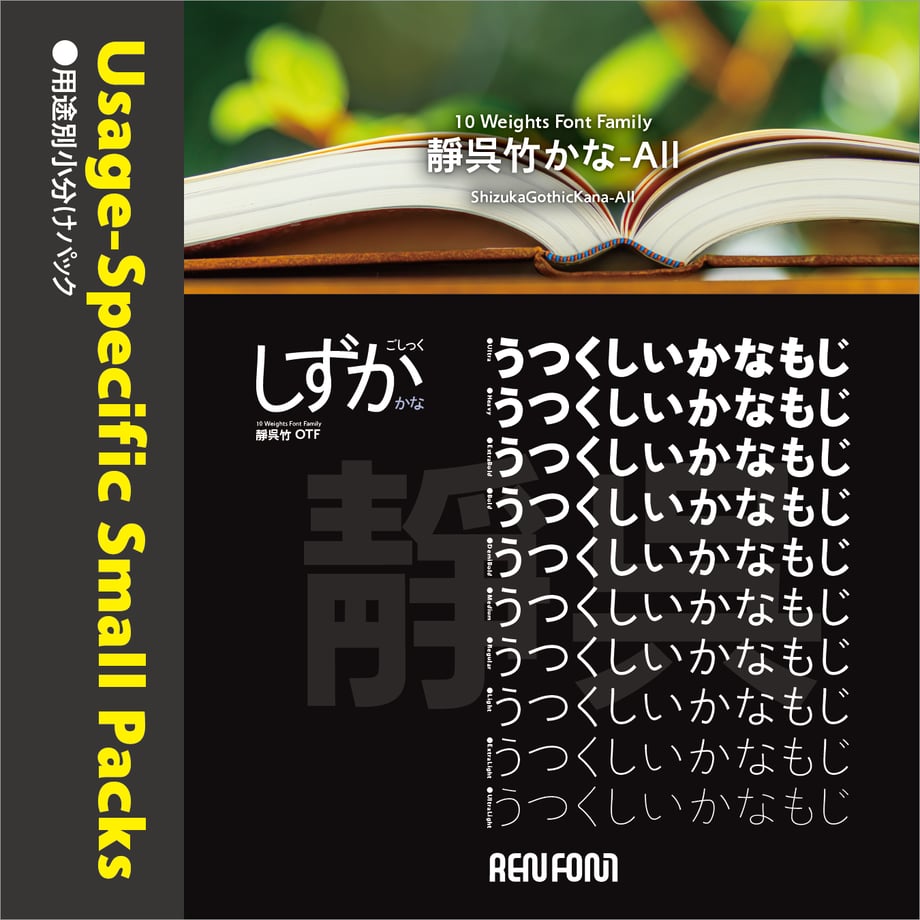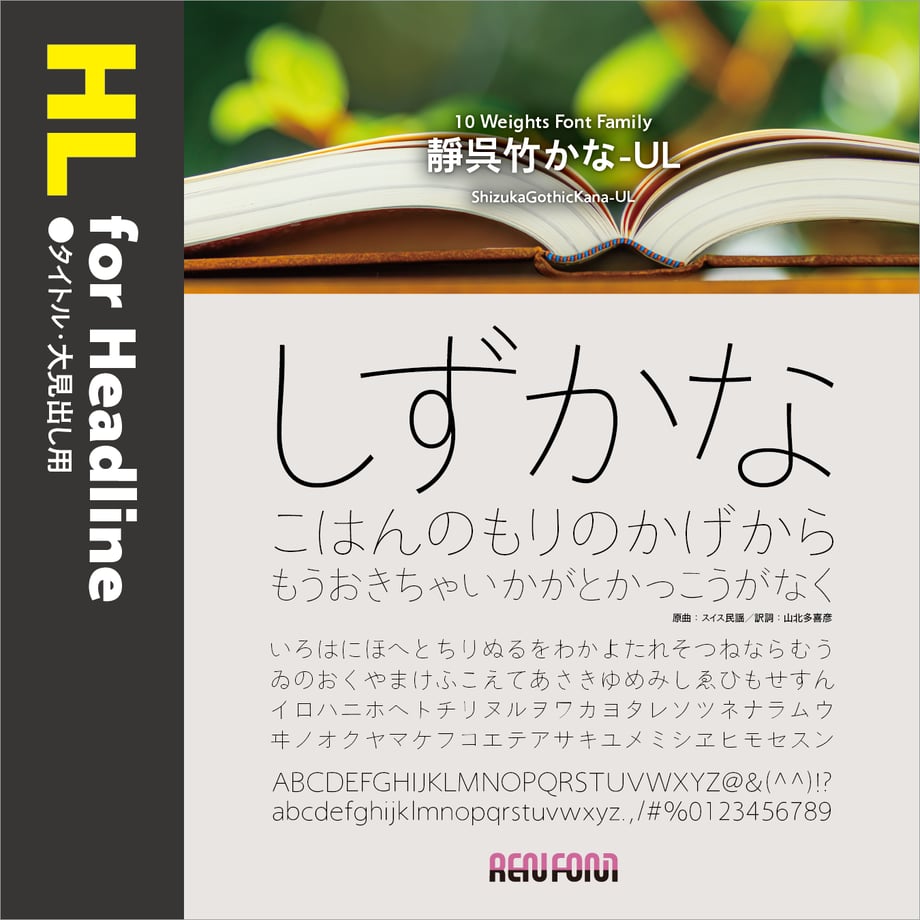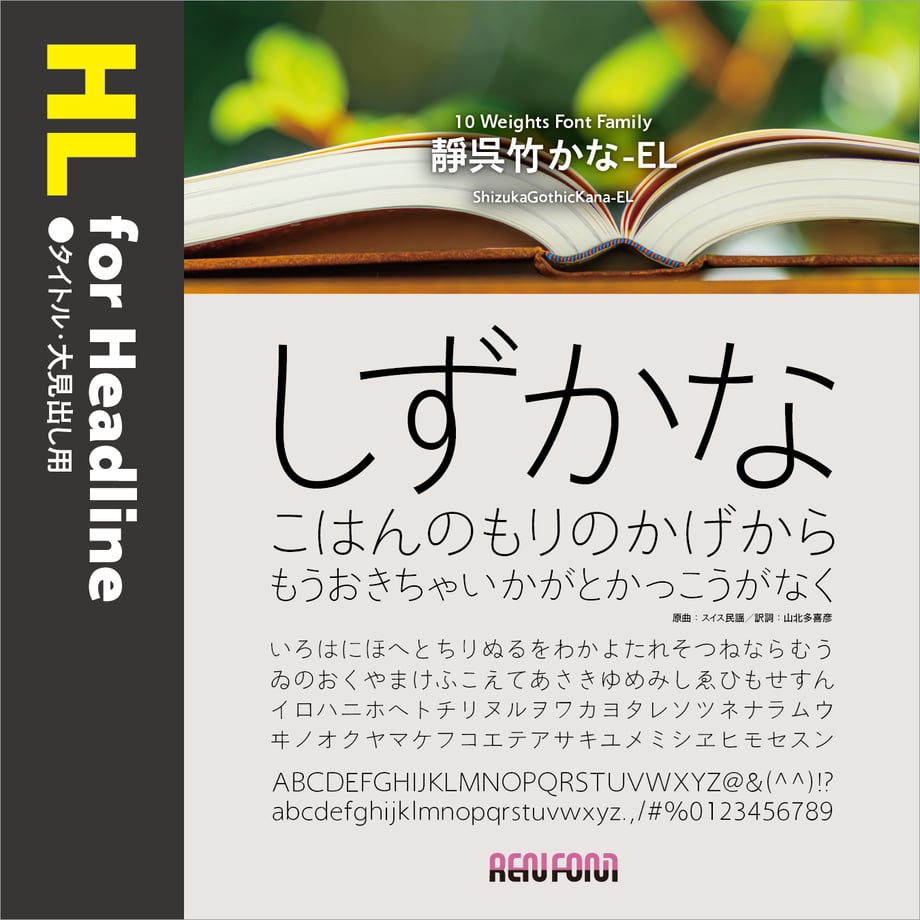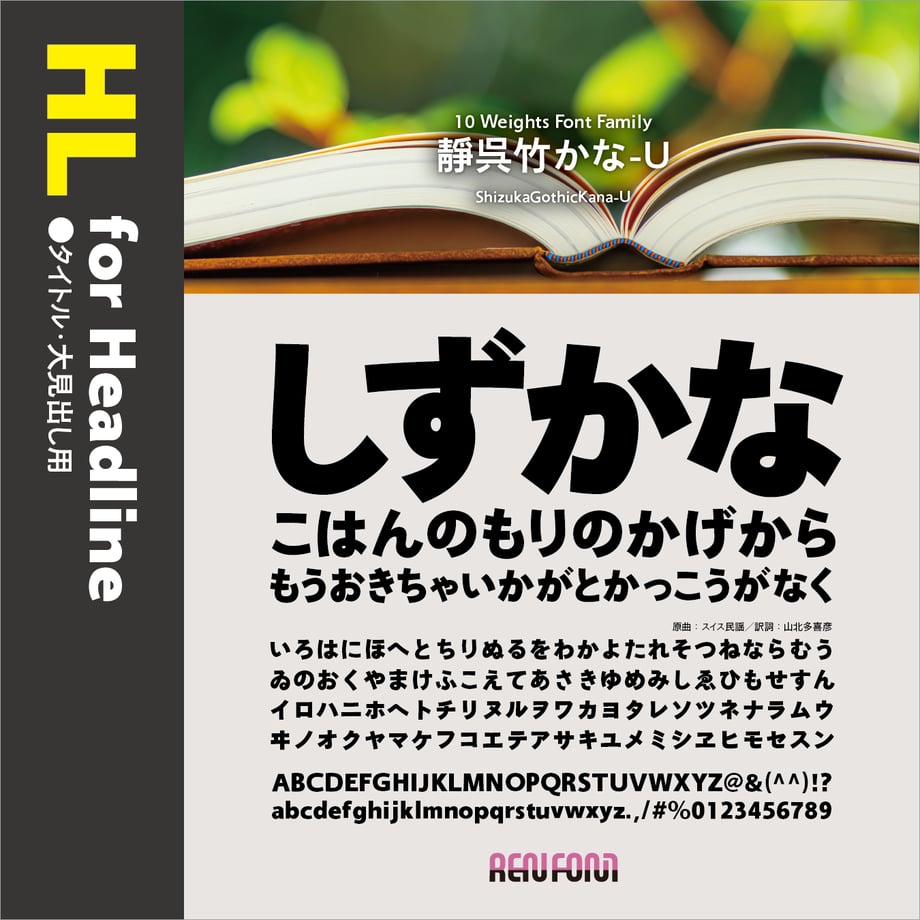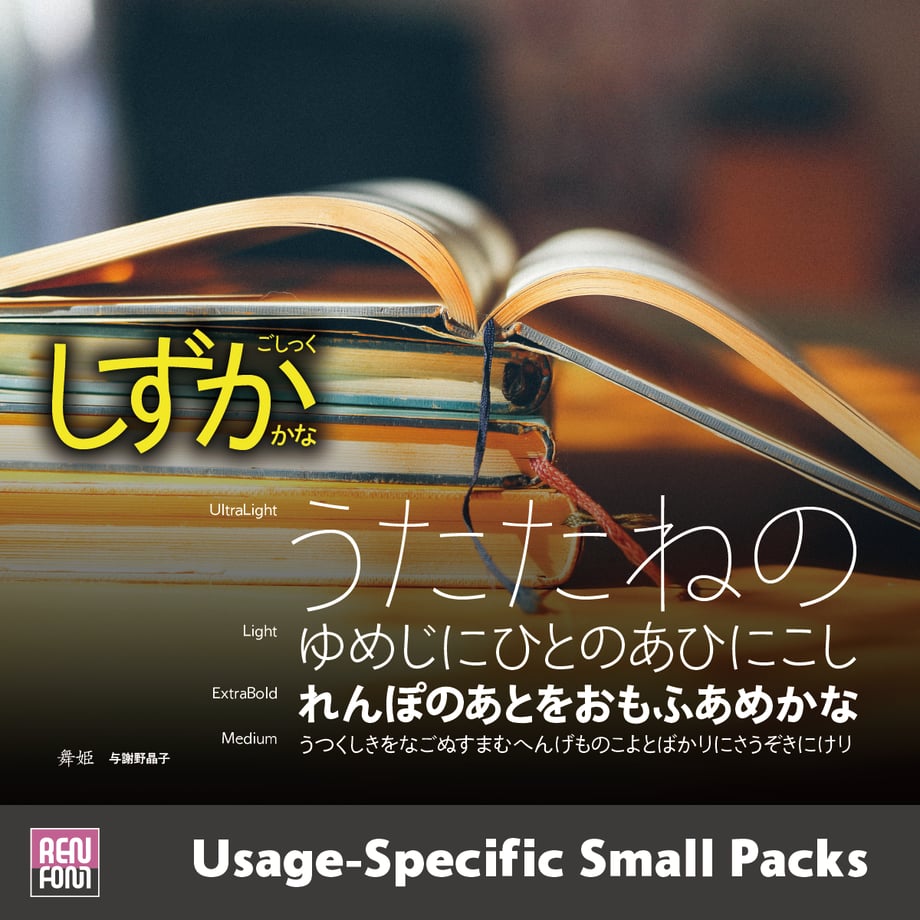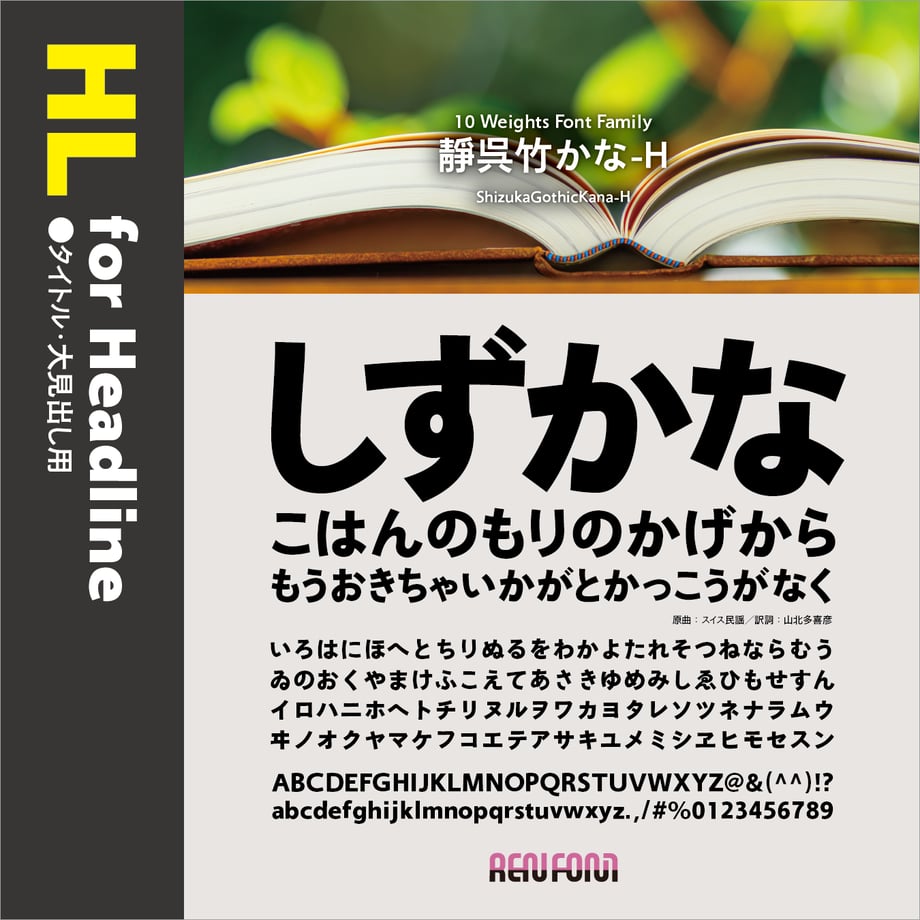
靜呉竹-HL(タイトル・大見出し用)UL/EL/H/U
ほんわかあたたかい書体
靜呉竹ファミリーの各書体は、読むことに専念してもらうために開発しました。書体に特徴を盛りこんでしまうと、読むことの妨げになることがあります。
この書体は、それを避けることに主眼を置きました。究極の“没個性”、それが靜呉竹です。
ちょっとかしこまった普段使いの文字を整理しフォントにしました。
勢いのある「勢蓮」とは何もかも対照的な控えめな書体。ゆえに「静(しずか)呉竹(ゴシック)」と名づけました。
「跳ね」「連綿」を極力抑えました。起筆部のアクセント(セリフ)もなくしています。
一画ずつ静かに、そして、ていねいな手書きにこだわりつつ、美しい伝統的書体寄りのフォルムに仕上げました。
本文組みに使ってみてください。ほんわかとした、あたたかく読みやすい文章になるはずです。
縦組み、横組みともプロポーショナル加工を加えています。また、横組みに限り(欧文も)、ペアカーニングもほどこしました。
●UL[ウルトラライト]
日本語文章の約70%はひらがな、カタカナが占めているといわれます。しかし、両仮名のみでは文章は成立できないのもまた事実です。それが、仮名書体の背負う宿命でもあります。
靜呉竹はウェイトが10もあります。UL・ELを揃えたことにより、AXISやヒラギノなどの極細ウェイトをもつ書体とも合成することができます。つまり、ほとんどの書体とのコラボレーションを可能にしました。
フォルムは「跳ね」「連綿」起筆部の「アクセント」をなくしました。下の4文字は書体によりかなり形状が異なりますが、靜呉竹は最低限の点・角に抑えスッキリとした雰囲気に仕上げました。
欧文・数字は、シンプルな両仮名に合わせて、クセの少ない伝統的なイメージにデザインしました。
格調高いMyriadに似た形状をしていますが、よりオールドな風合いの設計になっています。欧文書体としての単独使用にも十分に耐えうる、和文付嘱書体としては稀な、非常に高い完成度を持っています。